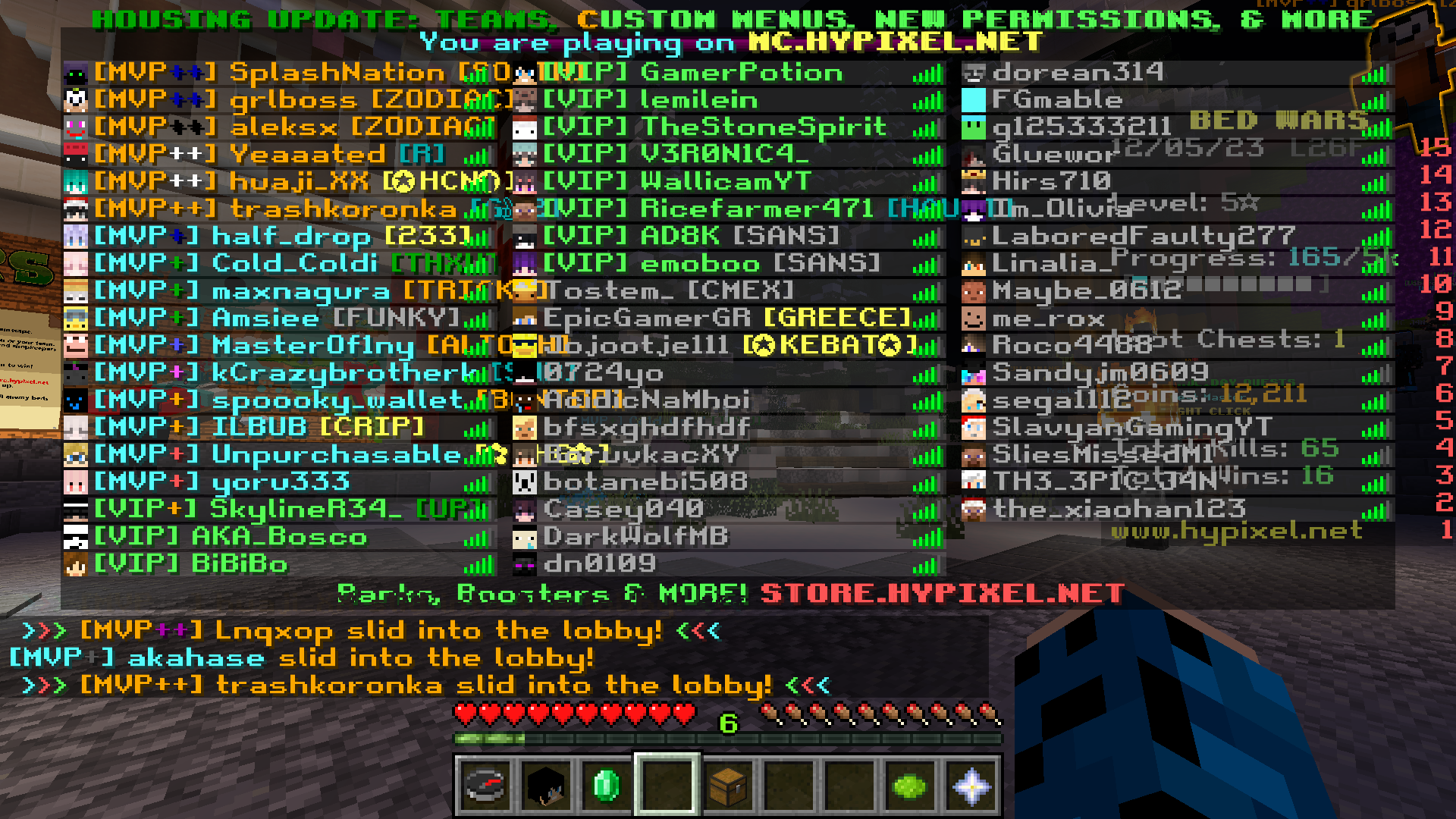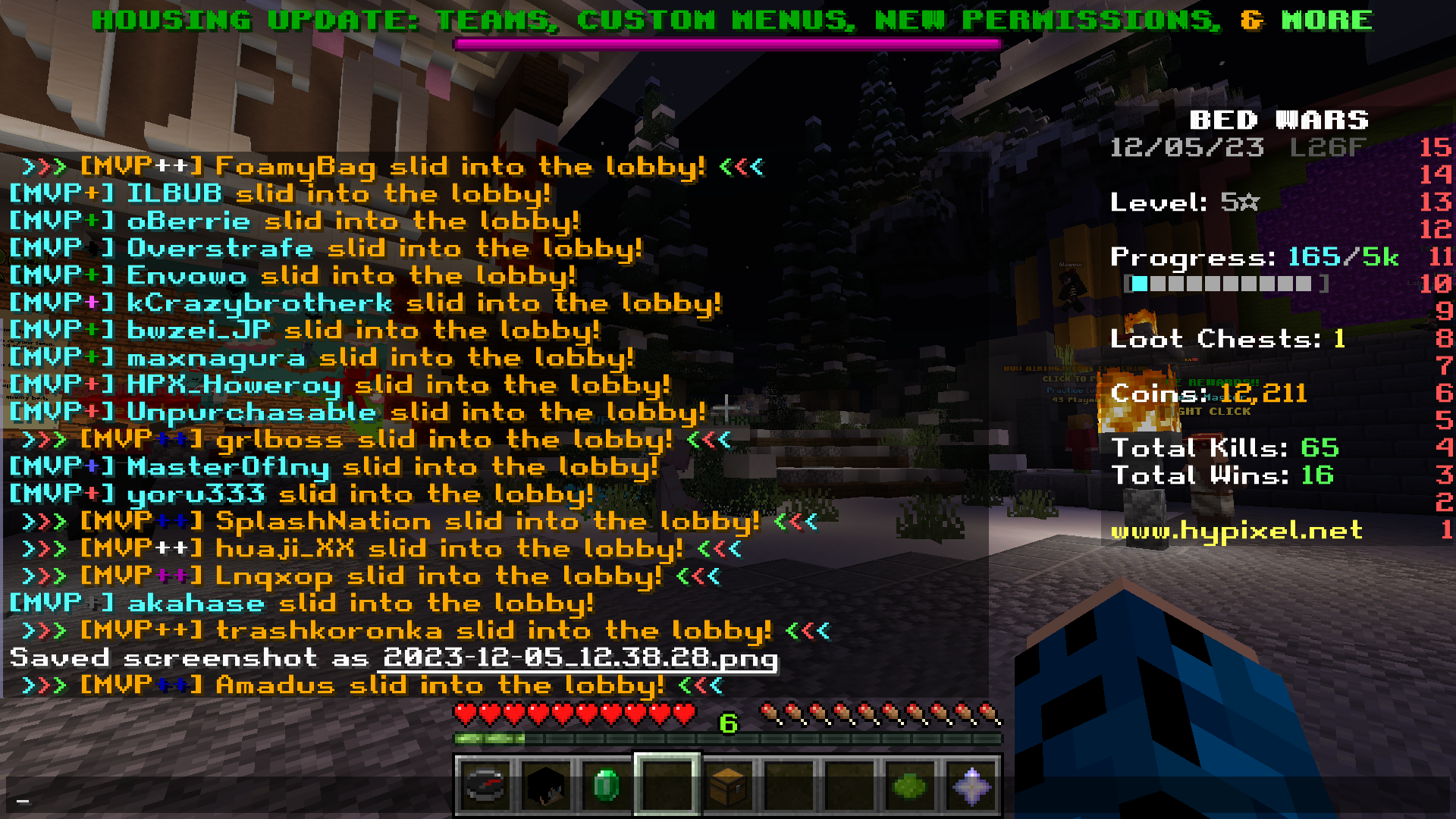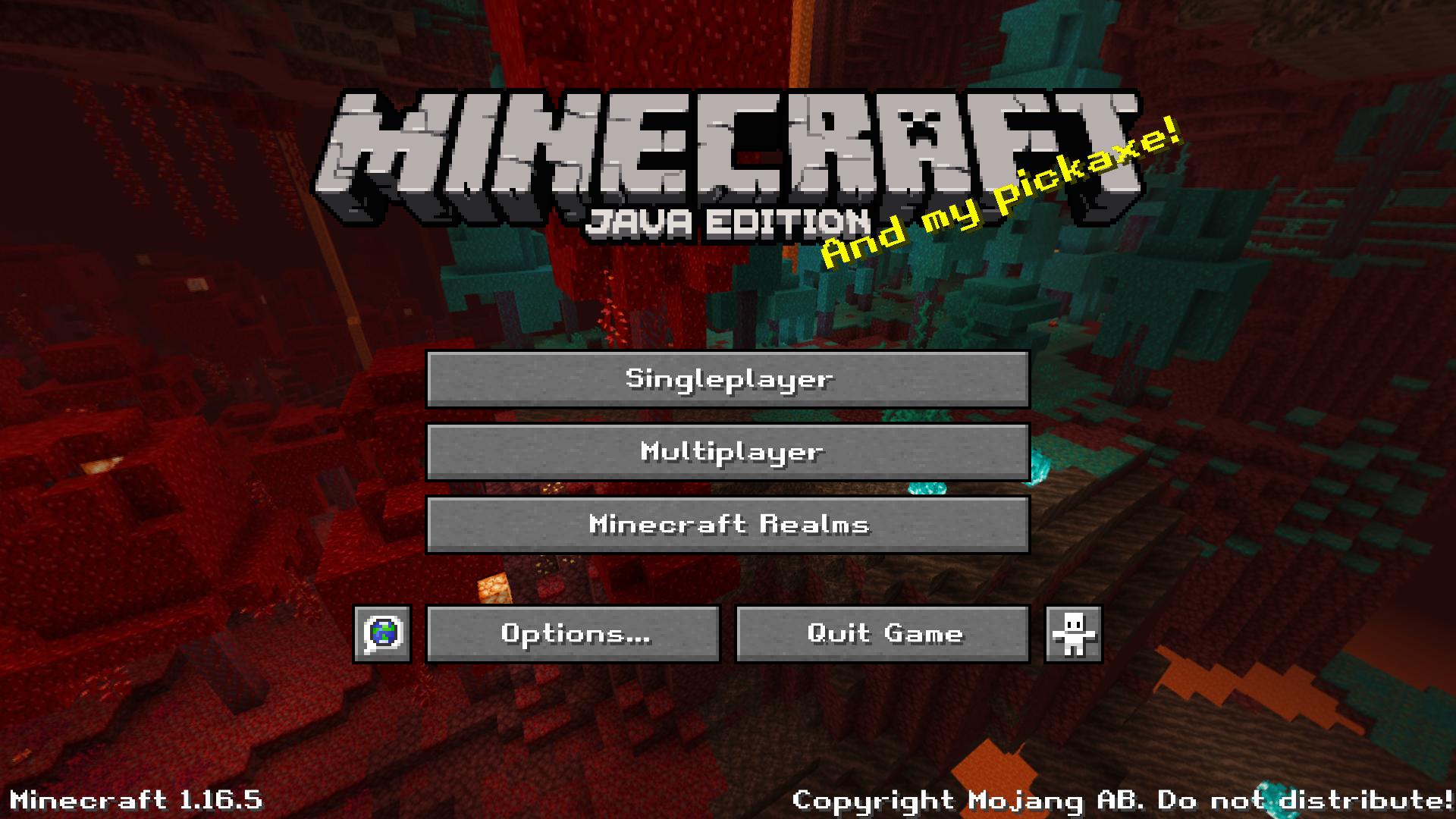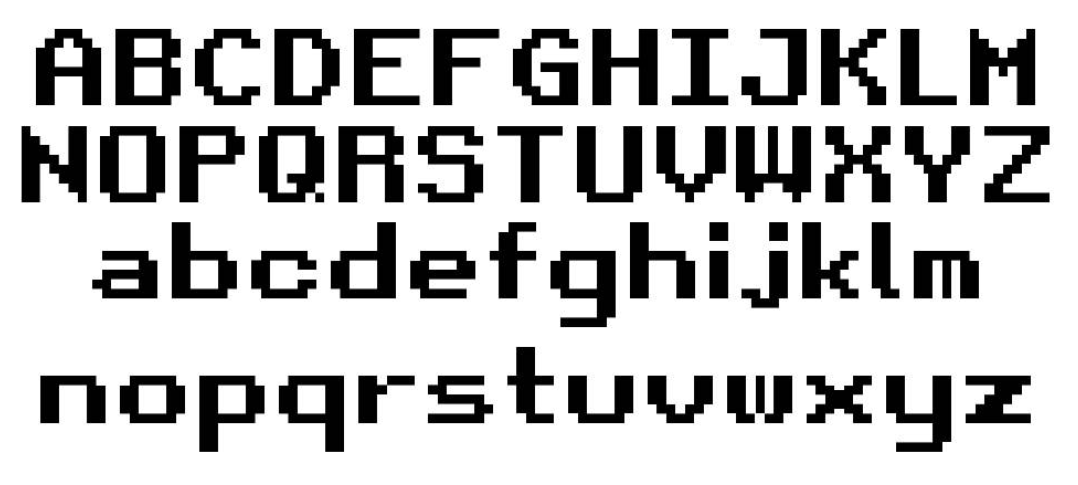
Retro RPG Font для Minecraft: Погружение в атмосферу классических RPG
Retro RPG Font — это уникальный шрифтовой пакет, который превращает стандартный текст Minecraft в стилизованное оформление из ретро-игр. Если вы любите классические RPG или хотите добавить в игру атмосферу старых добрых приключений, этот ресурспак станет отличным дополнением!
🔍 Что такое Retro RPG Font?
Этот пакет заменяет стандартный шрифт Minecraft на пиксельный стиль, вдохновленный ретро-играми. Основные особенности:
✅ Читаемость — шрифт сохраняет удобство восприятия, несмотря на стилизацию.
✅ Атмосферность — текст выглядит так, будто взят из классических RPG 90-х.
✅ Совместимость — работает как с ванильной игрой, так и с модами, включая DarkRPG.
🖼️ Как выглядит Retro RPG Font в игре?
(Описание изображения: Скриншот интерфейса Minecraft с ретро-шрифтом, напоминающим классические RPG. Текст в инвентаре, чате и меню выглядит стилизованным под пиксельную графику.)
(Описание изображения: Пример использования шрифта в модификации DarkRPG. Текст квестов и диалогов выглядит так, будто взят из старой консольной игры.)
🎮 Где лучше всего использовать этот шрифт?
Retro RPG Font идеально подходит для:
🔹 Ролевых модов (DarkRPG, MC Eternal, Roguelike Adventures).
🔹 Серверов с RPG-механиками (квесты, диалоги, лор).
🔹 Любителей ретро-стиля — если вам нравятся игры в духе старых Final Fantasy или Dragon Quest.
🏆 Почему стоит попробовать?
Если стандартный шрифт Minecraft кажется вам слишком простым, этот пакет добавит:
✔ Уникальную атмосферу — игра заиграет новыми красками.
✔ Ностальгию по классике — фанаты ретро-игр оценят.
✔ Улучшенное погружение — особенно на RPG-серверах и с модами.
🔥 Заключение
Retro RPG Font — это небольшое, но крутое изменение, которое может сильно повлиять на ваше восприятие Minecraft. Если вы фанат ретро-игр или просто хотите освежить интерфейс, обязательно попробуйте этот ресурспак!
(Описание изображения: Сравнение стандартного шрифта Minecraft и Retro RPG Font. Видно, как меняется атмосфера игры благодаря пиксельному стилю.)